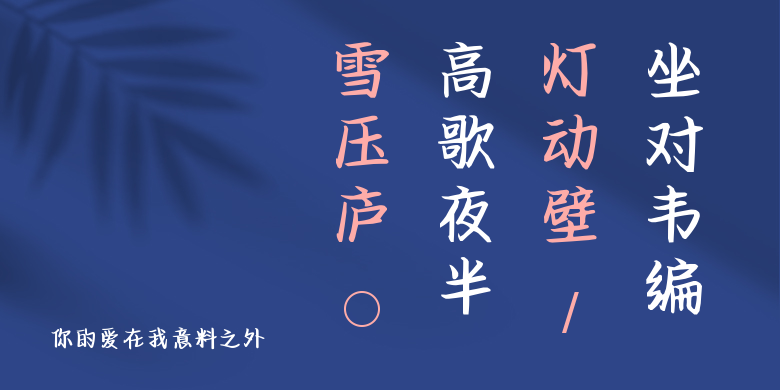
你的爱在我意料之外
你的爱在我意料之外,这款字体结构工整、笔画清晰,兼顾美观与易读性,适用于标题、正文、海报、包装、LOGO 等多种场景。字形优雅稳定,风格百搭耐看,适配日常排版与创意设计,让文字呈现更舒适、更具质感。你的爱在我意料之外一笔一画,皆是细节,以均衡的比例、流畅的线条打造舒适视觉体验,字形端正大气,风格简约现代。无论是商业设计、品牌宣传还是日常排版,都能轻松驾驭,让文字更有格调与力量。你的爱在我意料之外字体下载。